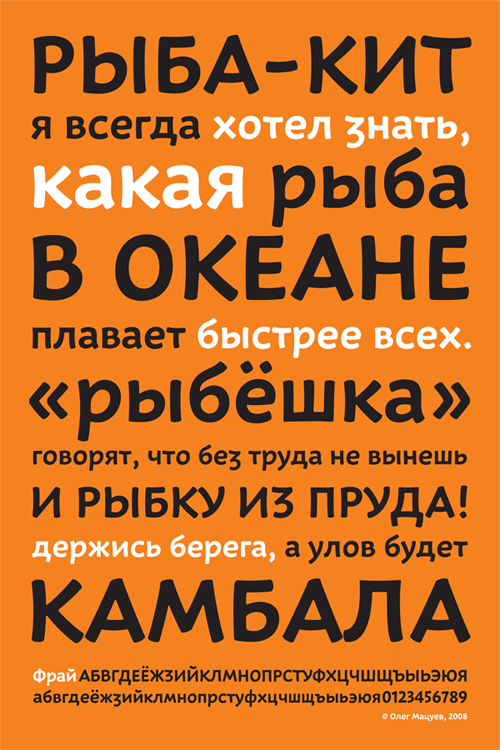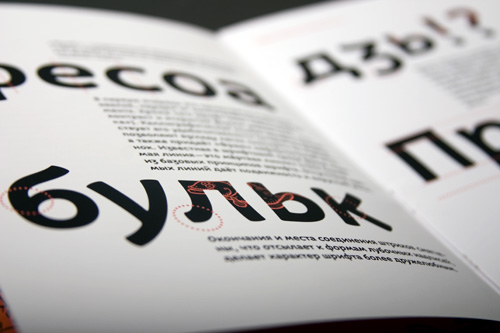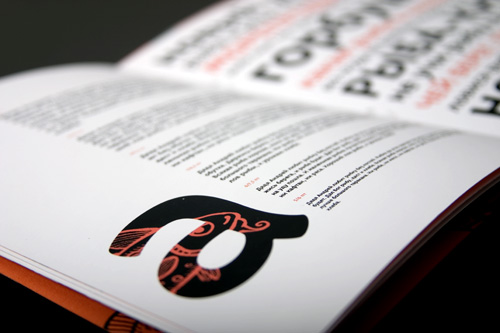
Fry
Шрифт Фрай (с англ.—«рыбёшка») разработан в студии FRONT:DESIGN специально для компании Sky-Fish (торговля рыбой и морепродуктами). Шрифт предназначен для коротких надписей и небольших текстов, имеет дружелюбный характер и лёгкий сказочно-исторический привкус (можно увидеть в несколько архаичных формах «д», «з»). Фрай взял открытость и динамичность от гуманистических гротесков, простоватость и мягкость от форм лубка, а подвижность от мелкой морской рыбёшки. Несмотря на разудалую весёлость, на упаковке Фрай прекрасно работает даже в 5-ом кегле. В крупных размерах Фрай проявляет свою оригинальность, живость и мягкость, в мелких же—характерные особенности становятся менее заметны и на первое место выходит его удобочитаемость, что делает шрифт подходящим для решения многих задач типографики.
Участник выставки шрифта и каллиграфии «Свято Кирилиці 2008». Победитель конкурса «Современная кириллица 2009».